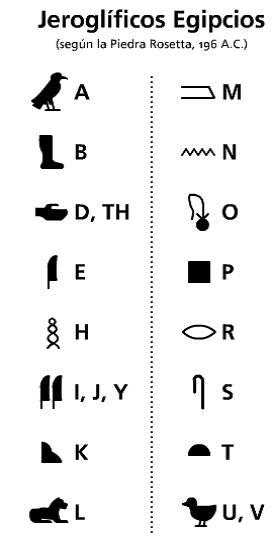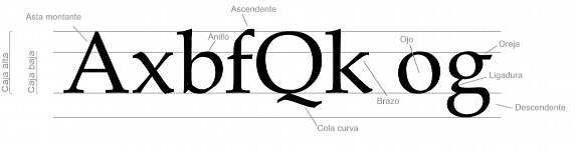
Tipografia
La tipografia
Tipografia
1. Aspecto historico
1. La tipografía es el fiel reflejo de una época.
1. El signo tipográfico ha sido miembro activo de los cambios culturales del hombre.
2. Letra
1. signo; representación gráfica del lenguaje hablado. Evolución de la escritura.
1. Tipografia
1. es el arte de diseñar letras y componer texto de tal modo que puedan leerse de un modo fácil, eficaz y agradable
1. Clasificacion de la tipografia
1. La presencia o ausencia del serif o remate
1. La forma del serif
1. ŸLa relación curva o recta entre bastones y serifs
1. ŸLa uniformidad o variabilidad del grosor del trazo
1. ŸLa dirección del eje de engrosamiento
2. 2 grupos fundamentales
1. Tipografías con serif
1. Tipografías sans serif o de palo seco
2. Partes de la letra
1. No existe una nomenclatura específica para designar las partes de una letra. Estos son los términos más actuales y más comunes
1. Astas
1. Astas montantes
1. anillo
1. Brazo
2. Cola
1. Ascendente
1. Descendente
1. Oreja
2. Ojo
1. Rebaba
1. Serif, trazo terminal, remate